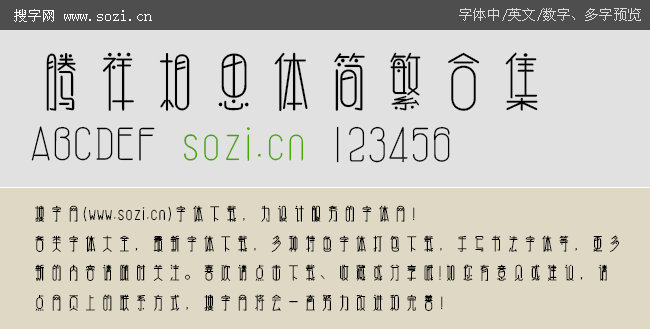
騰祥相思體簡繁合集
搜字網(wǎng)提供一款騰祥相思體簡繁合集中文藝術(shù)字體下載,,騰祥相思體為美術(shù)體。風(fēng)格采用方圓結(jié)合,字形為長方“口”“日”“目”等全部為圓 弧處理。結(jié)構(gòu)夸張、筆畫疏密相應(yīng),呈現(xiàn)字體輕松歡快的性格,散落在筆畫間的圓 點(diǎn)就好像一顆顆相思豆,顧名思義“相思體”。 本作品可用于出版印刷、廣告設(shè)計 網(wǎng)頁設(shè)計、包裝設(shè)計、屏幕顯示等領(lǐng)域。